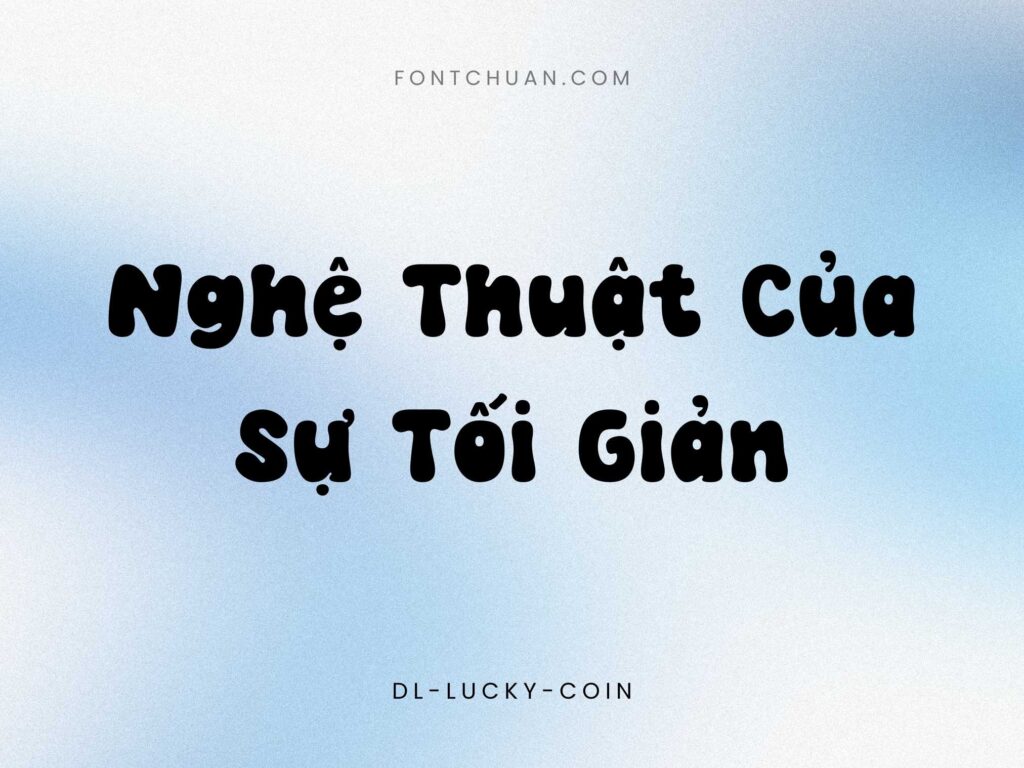
Font DL Lucky Coin Việt Hóa
Lucky Coin là một font chữ hiển thị đáng yêu và vui nhộn, được thiết kế bởi Dryy.type. Với các góc bo tròn và phong cách retro, font này mang đến sự tươi mới và linh hoạt cho nhiều dự án thiết kế khác nhau. Nhờ sự Việt hóa của Tduy, Lucky Coin hỗ trợ đầy đủ tiếng Việt, giúp người dùng dễ dàng ứng dụng trong các thiết kế đa ngôn ngữ. Thành viên của Font Chuẩn đã sưu tầm và chia sẻ font này để đáp ứng nhu cầu của cộng đồng thiết kế.
Về đặc điểm thiết kế, Lucky Coin sở hữu các ký tự đậm nét với đường cong mềm mại, tạo cảm giác thân thiện và vui tươi. Font này bao gồm các tính năng như chữ hoa, chữ thường, các ký tự thay thế và ligatures, mang lại sự đa dạng trong thiết kế. Lucky Coin đặc biệt phù hợp cho các dự án như thiết kế logo, poster, bao bì sản phẩm, thiệp mời và các ấn phẩm quảng cáo. Font này cũng thích hợp cho các sự kiện như sinh nhật, lễ hội và các dịp đặc biệt khác. Trong lĩnh vực ngành nghề, Lucky Coin được ứng dụng rộng rãi trong quảng cáo, thiết kế đồ họa, ẩm thực và thời trang, mang lại sự nổi bật và thu hút cho các sản phẩm và thương hiệu.